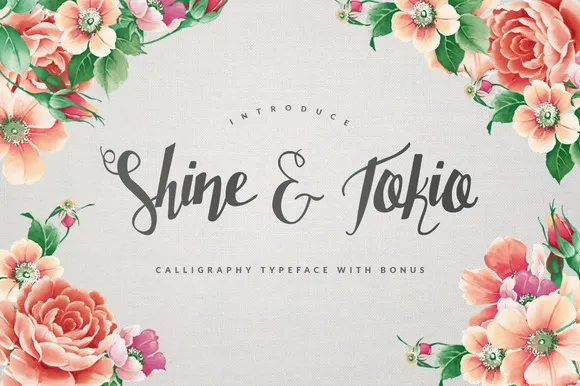
Shine & Tokio Typeface + BONUS – Fonte Grátis
Shine & Tokio Typeface + BONUS
A Shine & Tokio Typeface é uma fonte script que traz alegria com sua sensação natural forte. Ela parece pronta para atrair qualquer mensagem e dar um toque pessoal, sem sair do estilo elegante dos caracteres serifados. É especialmente adequada tanto para projetos vintage quanto modernos, sendo perfeita para aplicar em trabalhos de design artesanal como desenhos a tinta água, cartões de aniversário, panfletos e roupas personalizadas. Suas linhas finas e sua expressividade garantem que ela seja uma ótima escolha para diversos projetos gráficos. Seja você um designer vintage ou moderno, Shine & Tokio é ideal para criar mensagens que se conectam com seus espectadores de maneira direta e emocional. Além disso, ela oferece flexibilidade para personalizar a aparência do texto, permitindo que você use-a em qualquer aplicação desejada, como branding ou outros projetos gráficos, proporcionando um toque único e autêntico aos seus trabalhos.